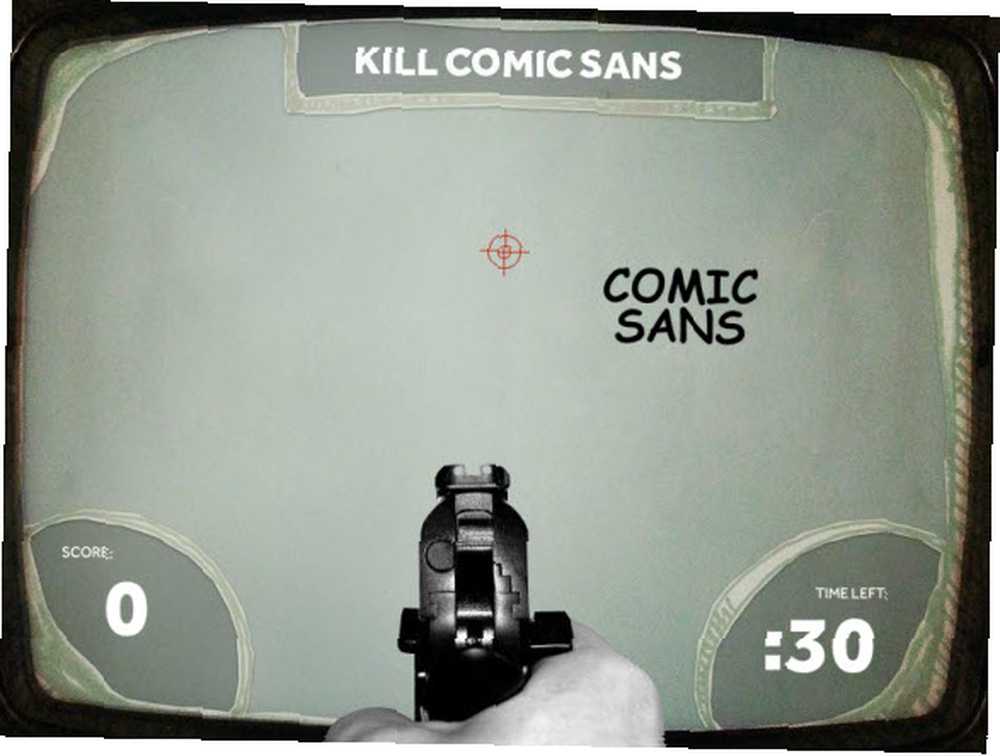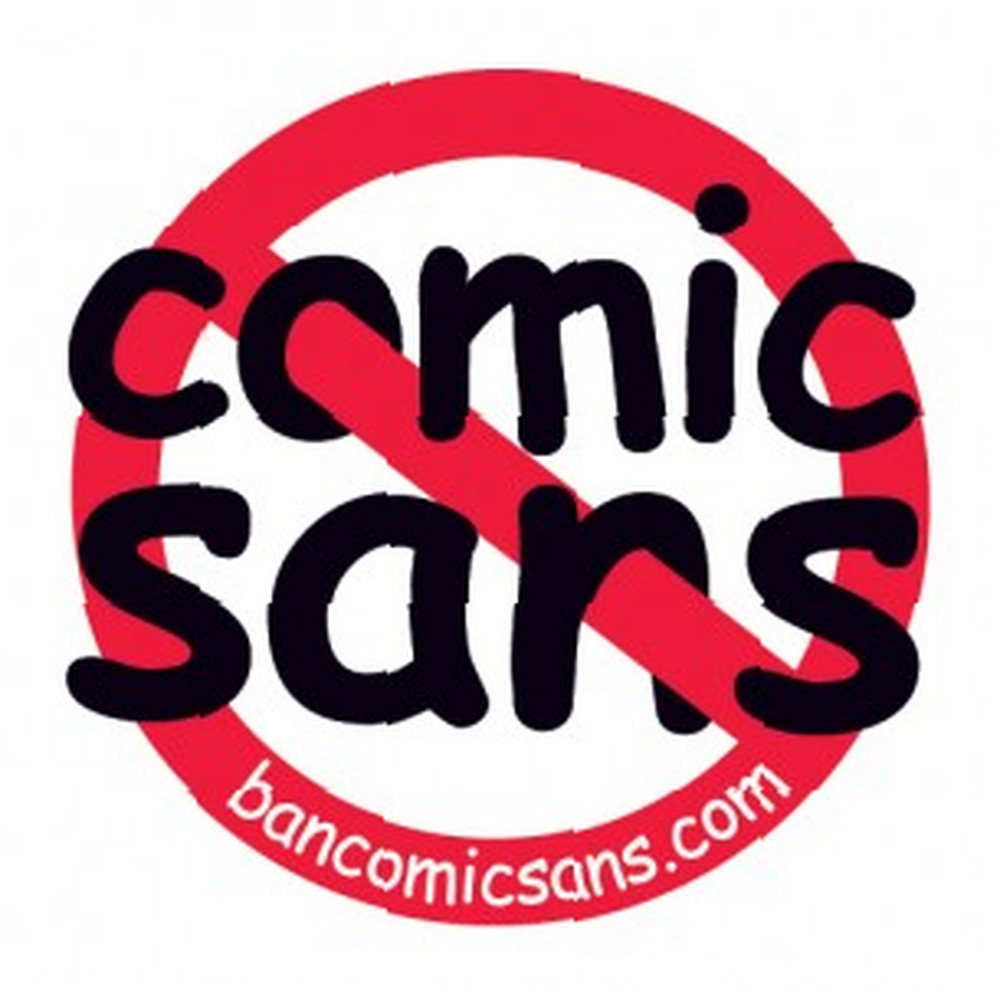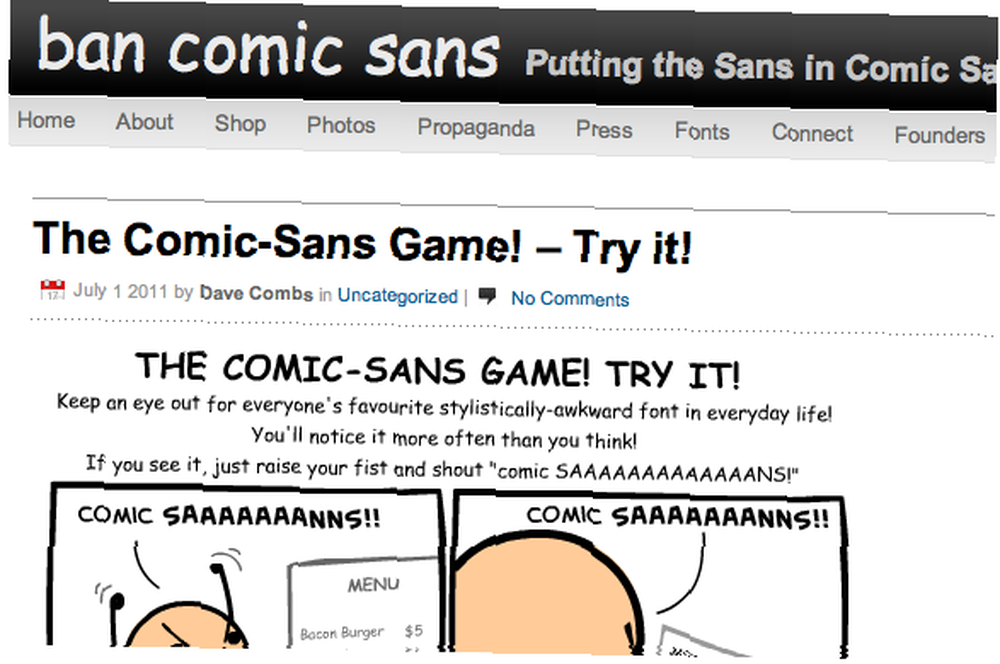
Il semble que peu importe où vous vous trouvez, il y aura toujours une forme de mot imprimé dans votre champ de vision. Avec autant de mots qui circulent, les concepteurs veillent à ce que leurs mots se distinguent de la foule par le biais de polices stylistiques. 10 polices fraîches pour ordinateur gratuit qui vous permettront de vous démarquer 10 polices d 'ordinateur gratuites superbes qui vous permettront de vous démarquer. Mais nous avons ensuite les utilisateurs de Comic Sans. Pour une raison quelconque, les gens insistent toujours pour placer cette police surutilisée sur les affichages de texte les plus étranges aux endroits les plus inappropriés. Cependant, un certain nombre de personnes sont prêtes à mener le combat et à mettre un terme aux abus de Comic Sans. Vous pouvez être l’un d’entre eux en consultant ces trois sites.!
Ban Comic Sans [N'est plus disponible]
Ici, nous avons le site qui a tout commencé - Ban Comic Sans. Commencé par Dave et Holly Combs (tous deux designers prolifiques), le couple s’est lancé en 2002 dans le but de: “remettre le sans dans Comic Sans.” À première vue, le site dispose d'un blog semi-dédié entièrement consacré à la suppression de Comic Sans de tous les affichages textuels du monde entier. Pour prouver son point de vue, le couple Combs a même installé une section de son site fournissant plusieurs exemples de Comic Sans misusage . En plus de cette présentation photo Flickr de la police dans la vie quotidienne, le site propose le court documentaire suivant de 8 minutes (présentant les versions Comic Sansified de logos et de marques courants) sur la police ainsi qu’un manifeste de typographie ferme..
Comic Sans Criminal
Il s’agit plus d’un site à utilisation unique, dans la mesure où il ne sert vraiment à rien d’autre que ce qu’il est déjà, mais même ainsi, Comic Sans Criminal a le potentiel d’être le cadeau qui continue de donner. Fondamentalement, le site est consacré à évangéliser la vérité sur les abus commis par Comic Sans à ceux qui y participent.. À leur arrivée sur le site, les utilisateurs sont accueillis par une page indiquant simplement, “Tu es un Comic Sans Criminal, mais nous sommes là pour t'aider.” Donc, si vous voyez quelqu'un utiliser la police redoutée, vous devez rapidement lui envoyer le lien, en le notifiant de son état criminel. Après avoir cliqué sur l'écran suivant du site, ils seront traités dans un diaporama intégré au navigateur soulignant les effets négatifs de Comic Sans..
Cependant, le site indique qu'il existe quelques raisons pour lesquelles utiliser Comic Sans peut être relativement raisonnable. Outre son utilisation par un public de moins de 11 ans et par la bande dessinée, le site indique que de nombreux dyslexiques trouveraient la police plus facile à lire qu’autre chose. En fait, pour plus d’informations dyslexiques, le site Web fournit un lien vers Dyslexic.org.
Tout sur Comic Sans Criminal est très ironique, mais il fournit quelques points légitimes. Par exemple, des articles tels que les défibrillateurs ne devraient jamais être étiquetés dans Comic Sans, alors je suppose que vous pourriez dire que l'utilisation correcte de la police (ou son absence) pourrait sauver une vie.
Blambot
Blambot n’est certes pas un site anti-Comic Sans, mais il offre plusieurs alternatives gratuites aux polices de style bande dessinée. Le site propose un petit quelque chose pour tout le monde, en gardant à l’esprit le fait que les bandes dessinées ont souvent besoin d’un lettrage différent pour des buts différents (non, Comic Sans ne peut pas être utilisé à des fins publicitaires). tout). Le site comporte trois classifications: polices payantes en édition limitée, polices payantes et, heureusement, une excellente sélection de polices gratuites. Je sais que cela peut paraître surprenant, mais il existe de nombreuses polices autres que Comic Sans. En fait, Blambot a une police de caractères différente pour chaque usage, que ce soit pour le dialogue, les effets sonores, la conception de base ou même des symboles loufoques..
Conclusion
Comic Sans n'est pas si mauvais que ça, mais il peut certainement en abuser ou en abuser. Heureusement, les trois sites ci-dessus fournissent des informations sur l'utilisation correcte de la police, ainsi que de nombreuses alternatives saines. Certes, si vous vous sentez angoissé et plein de révolte hardcore, vous pouvez jeter un coup d'œil à Kill Comic Sans, un jeu de tir d'arcade frustrant qui met l'accent sur l'incapacité des gens légers (mais méchants). Police de caractère. Quels cas avez-vous déjà vu abuser de Comic Sans? Quelles sont certaines de vos polices préférées?